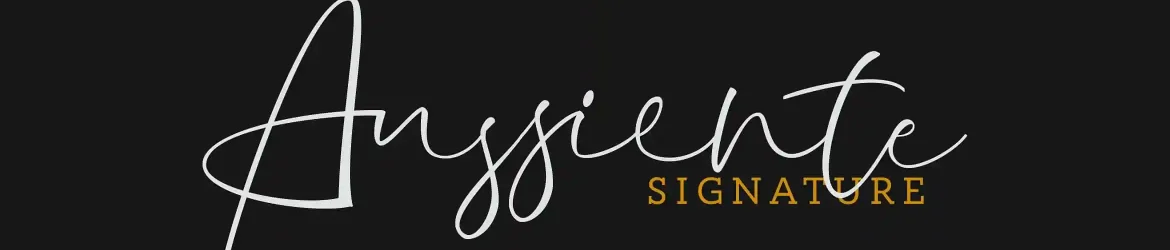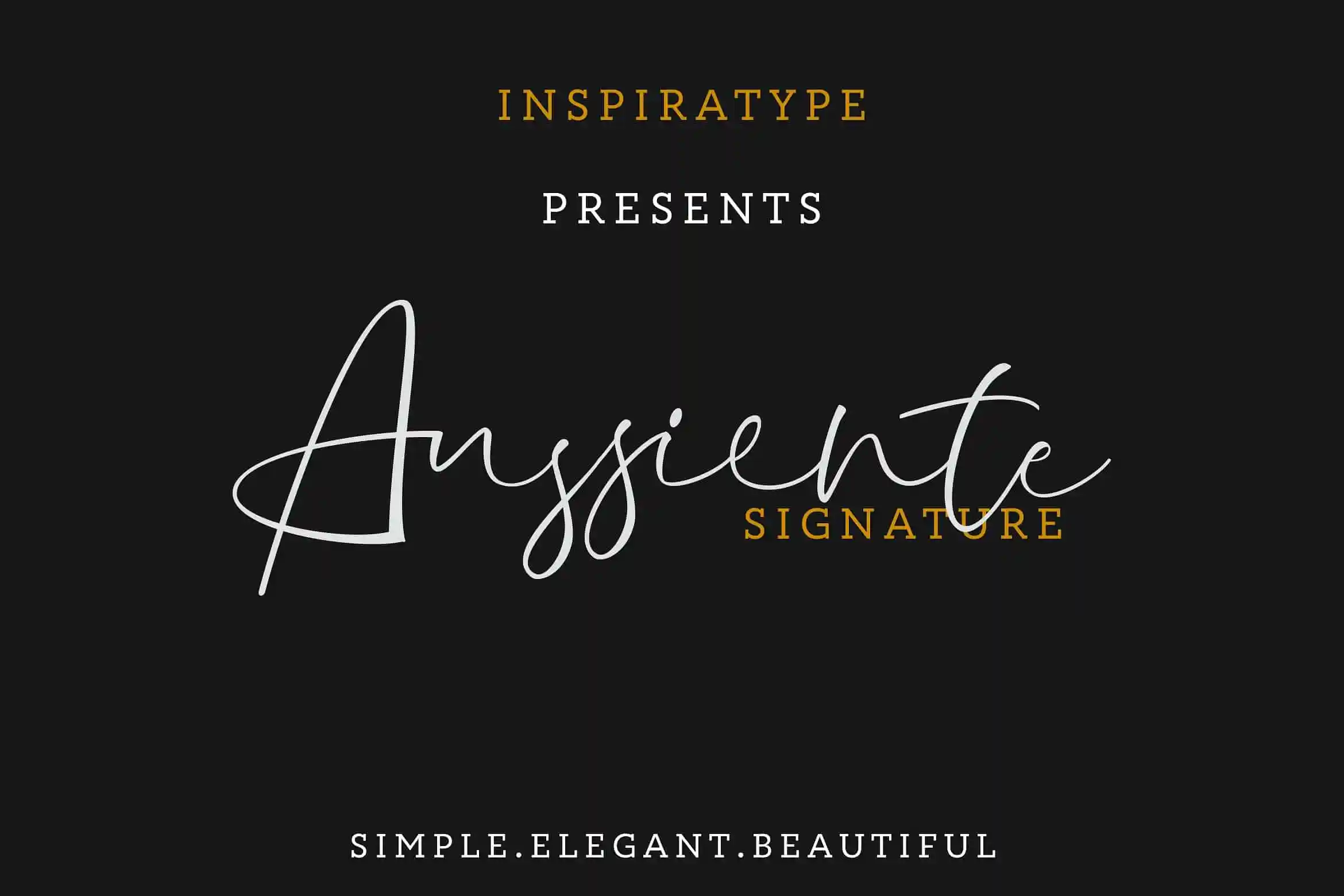
Aussiente Signature Font
Olha aqui, fonte apaixonante para você! Nossa nova apresentação é a Aussiente Signature Font, uma fonte à mão que inspira-se nas clássicas propagandas. Criada com habilidade humana e feita para revolucionar seus projetos de design! Esta fonte vem completa com letras maiúsculas e minúsculas, números e sinais de pontuação, mas oferece muito mais – você encontrará alternativas do tipo opentype, ligaturas comuns e até mesmo novas formas de cada caractere para que possa personalizar seus projetos conforme necessário. Perfeita para criar logotipos, cartões de visita, outdoors, roupas design, etiquetas e muito mais! Seja você um criativo ou estabelecido, a Aussiente Signature Font é uma opção de fonte autêntica que se destaca e fará sua marca ser única.